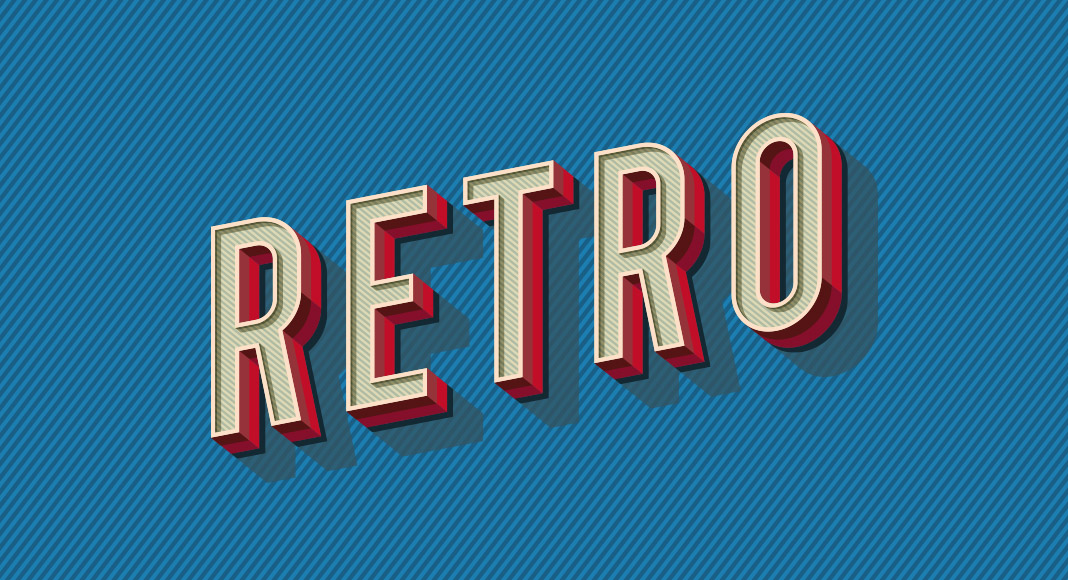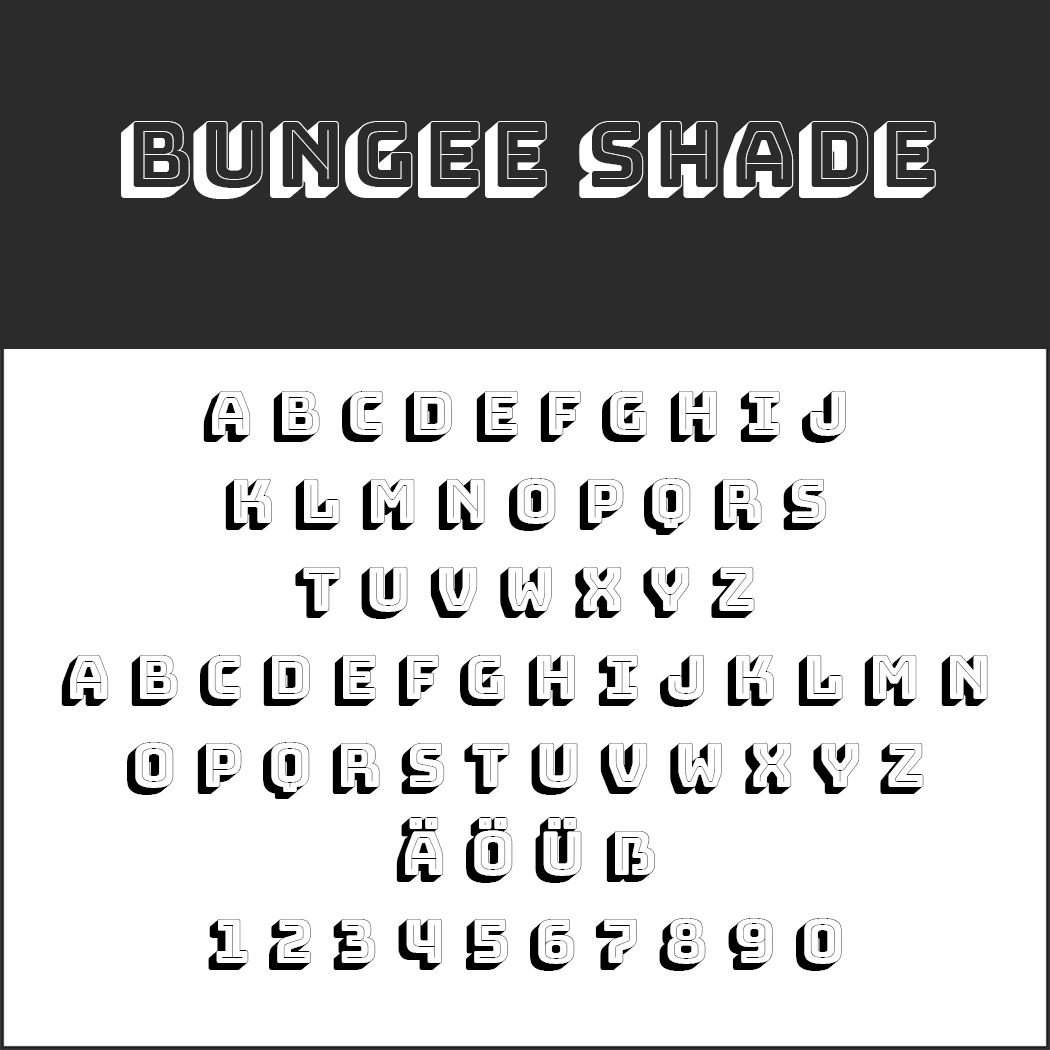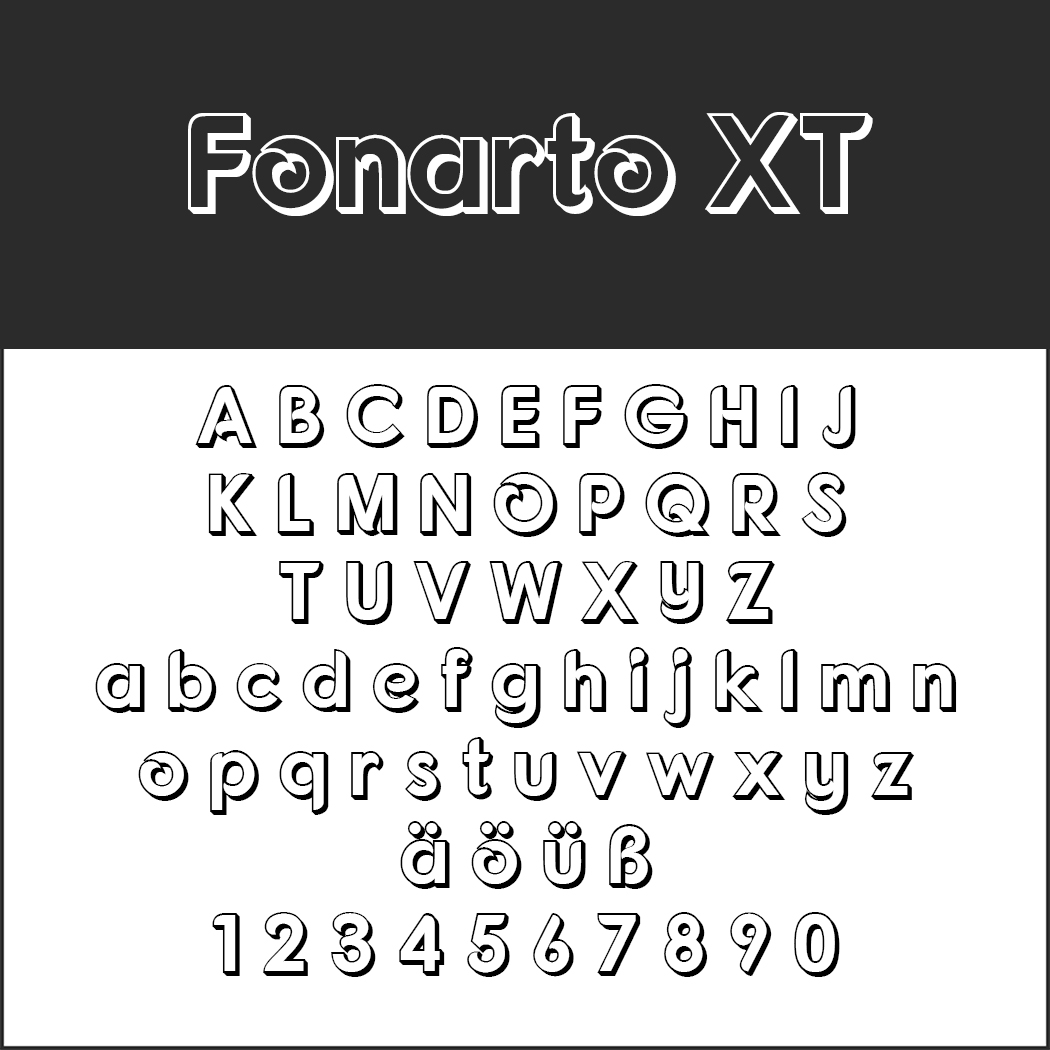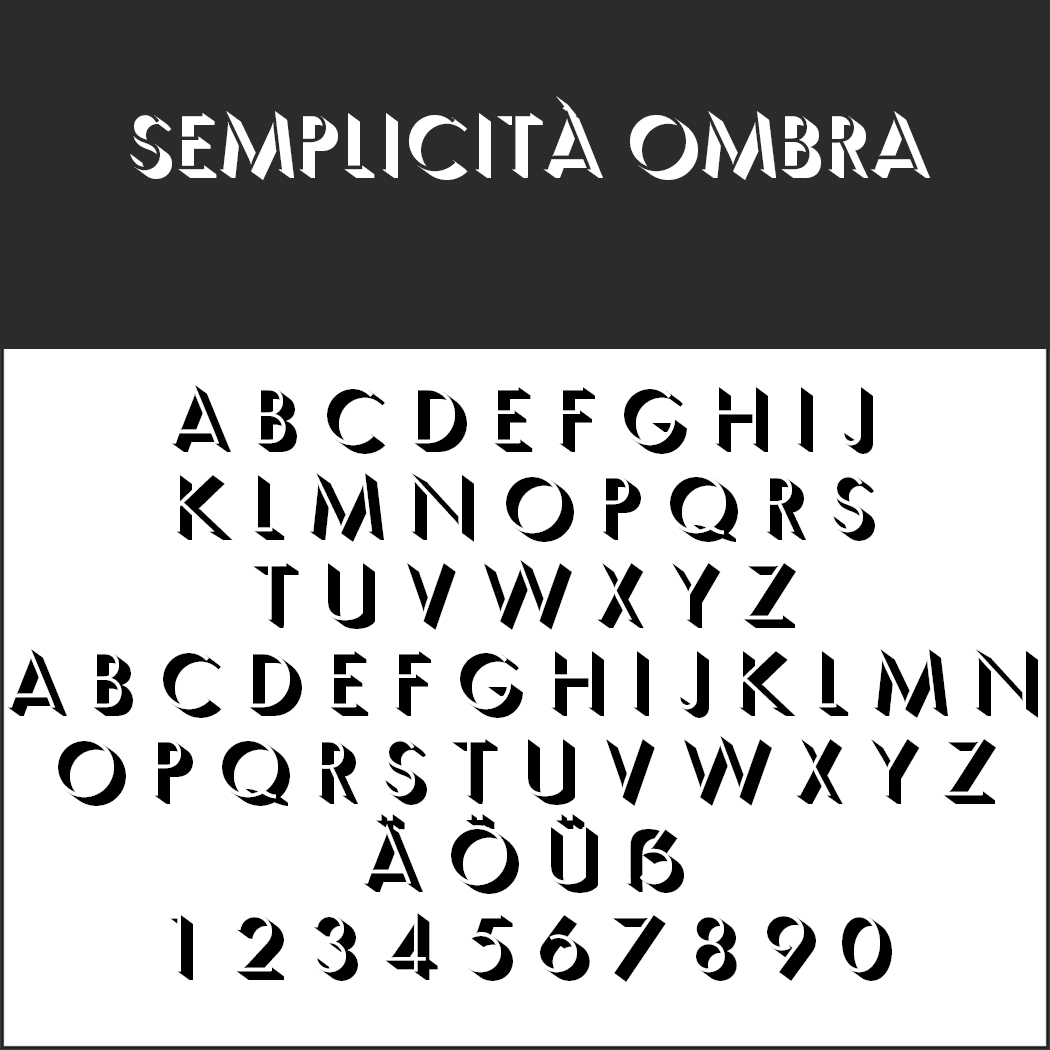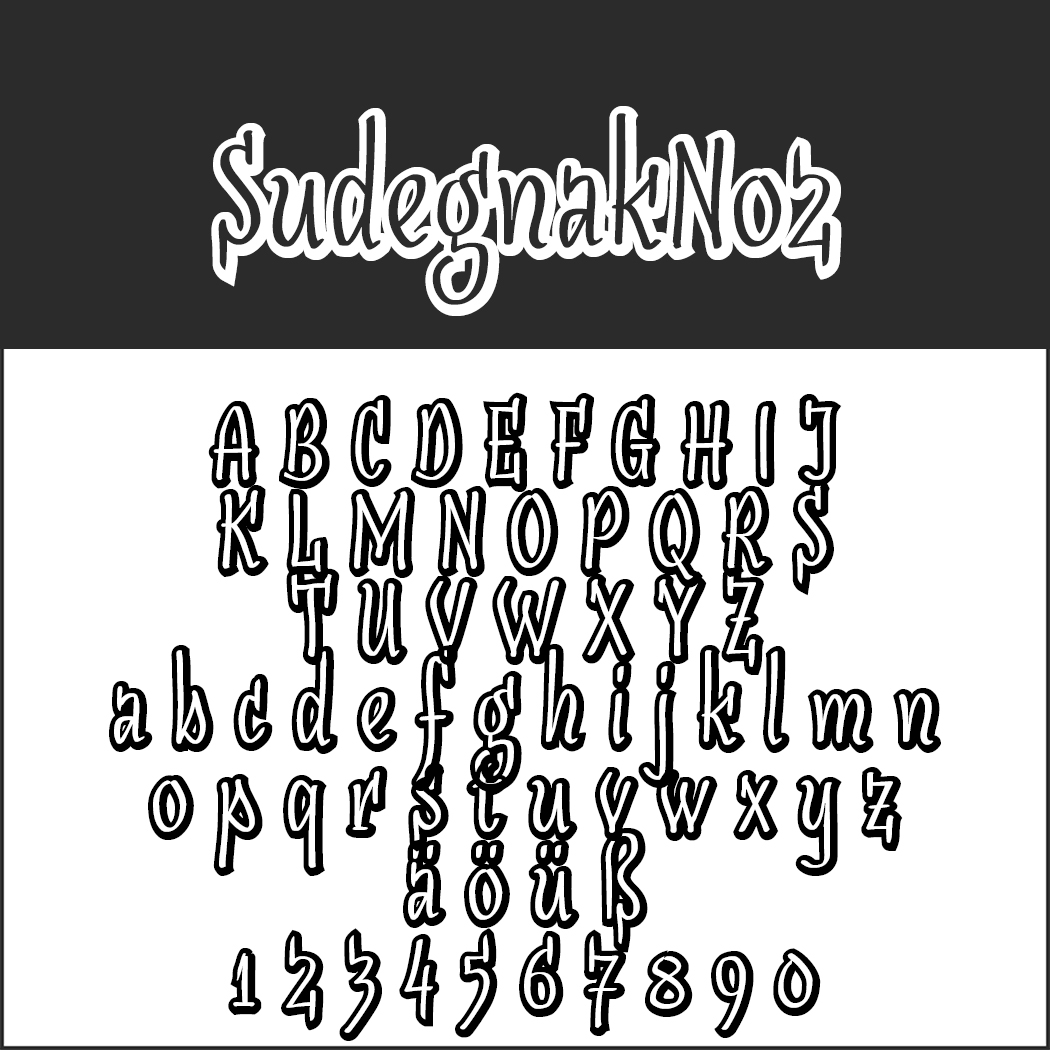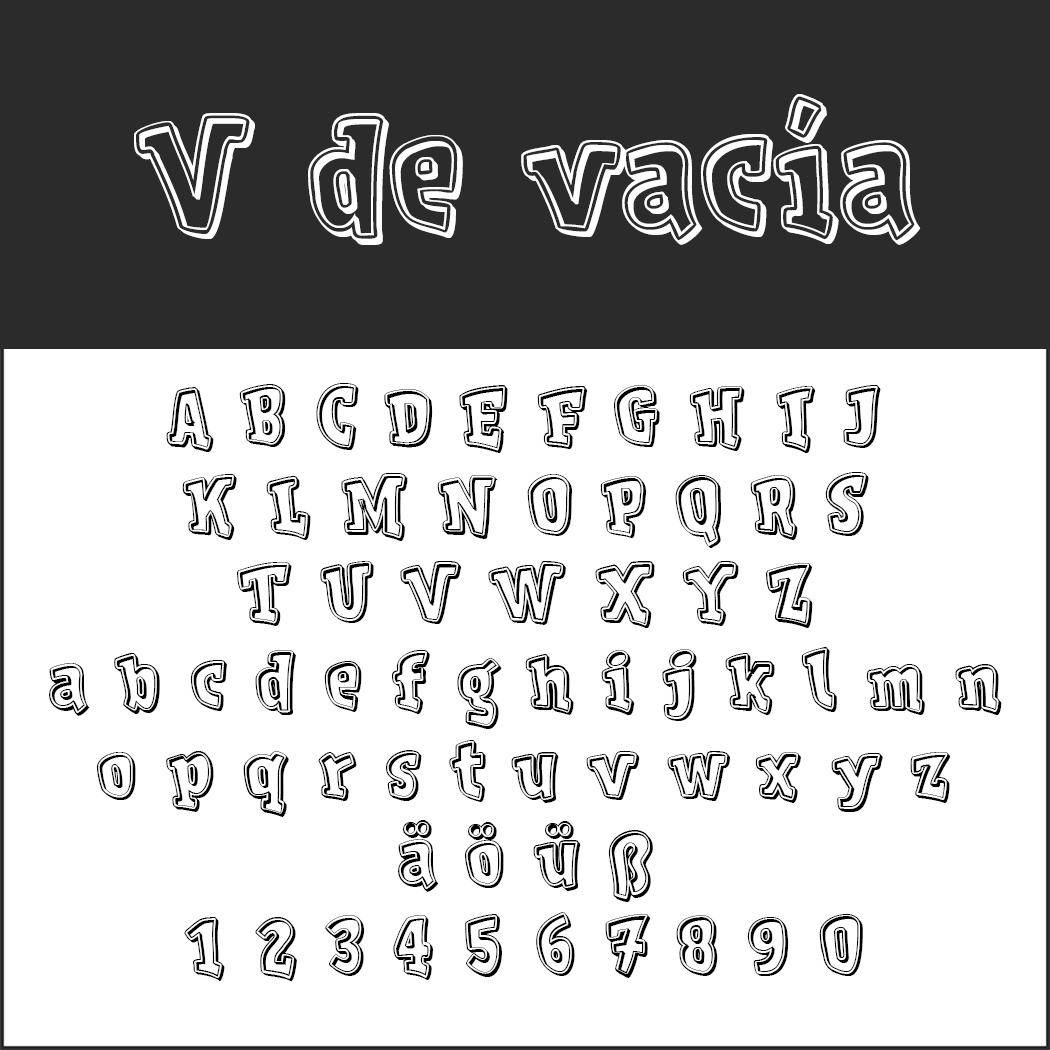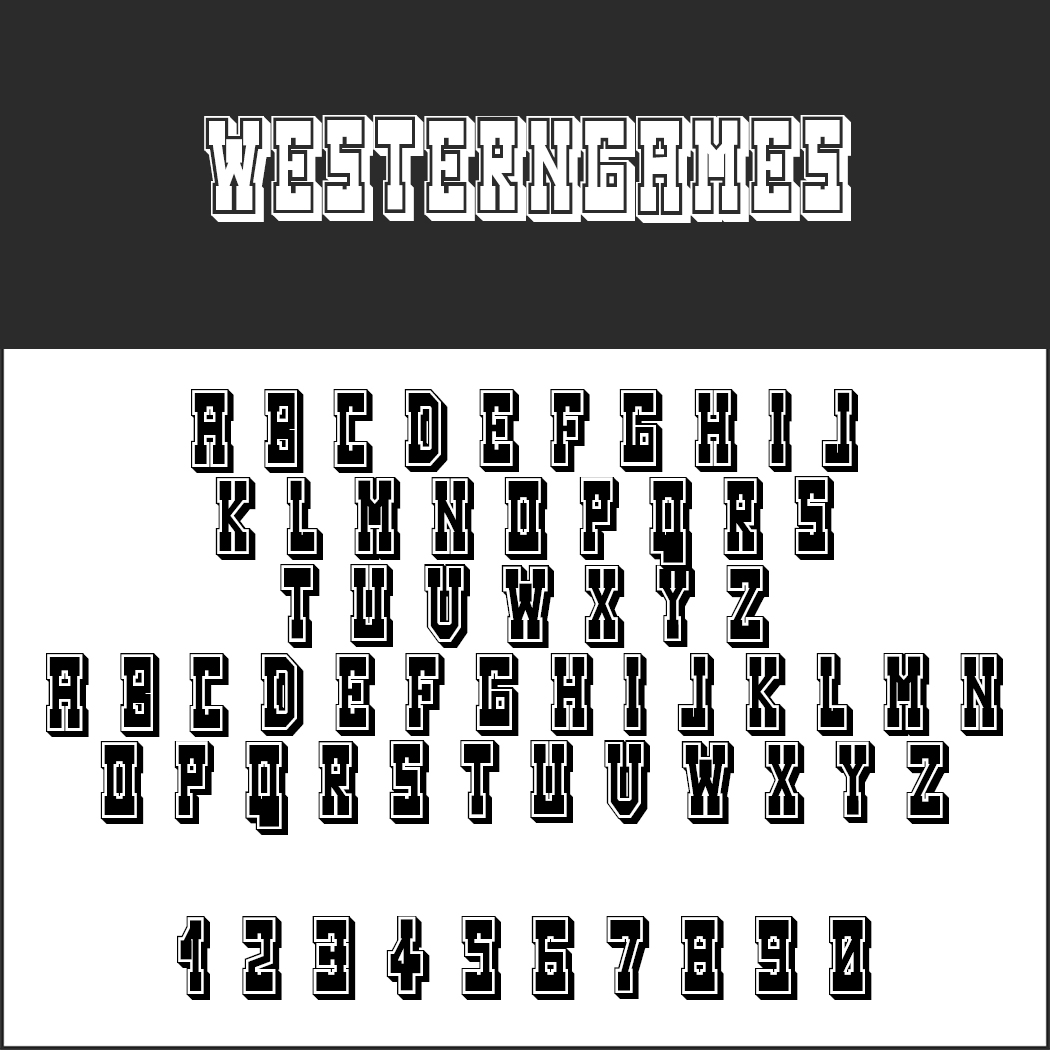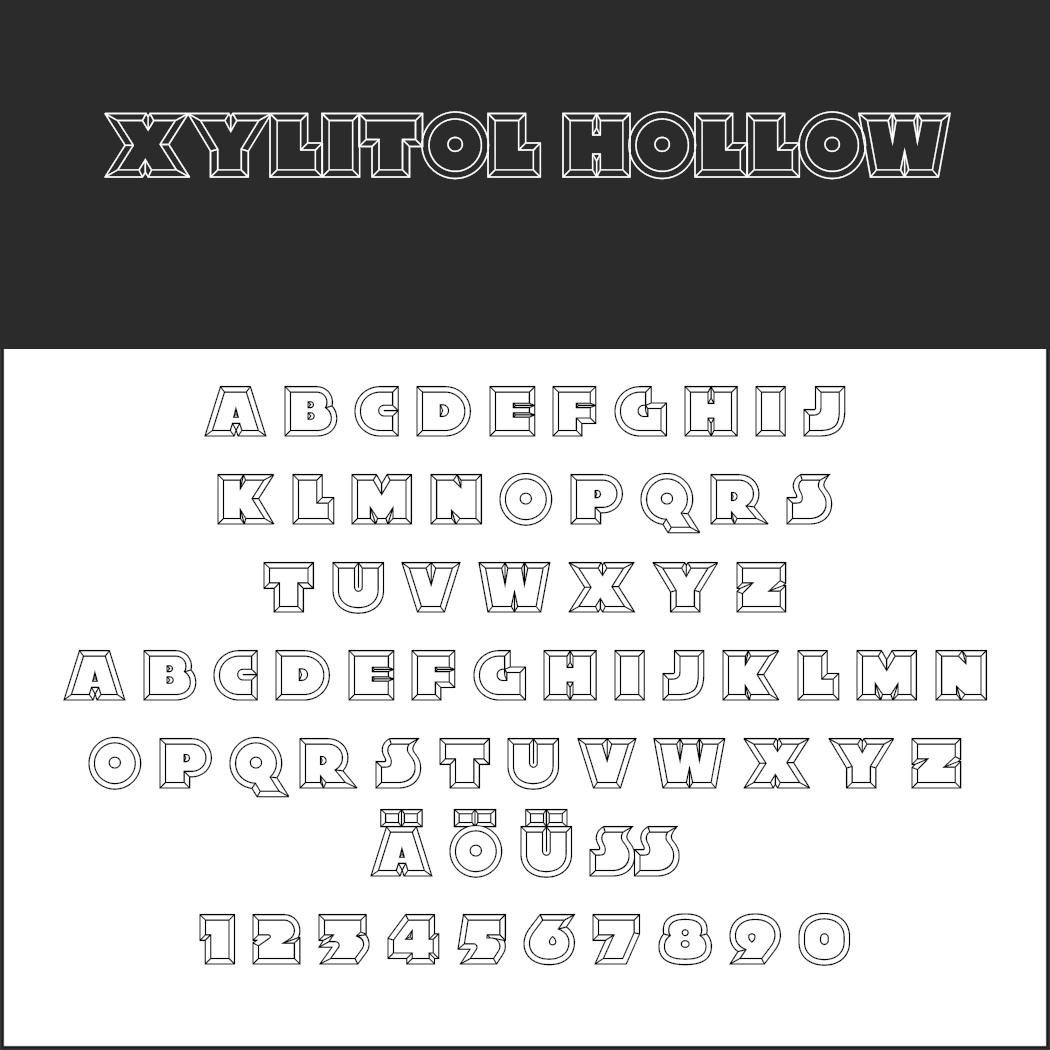
Korte budskaber vækker særlig opmærksomhed, hvis de består af tredimensionelle bogstaver. På papiret præsenteres de nemmest med en passende 3d font. Men med 3d font generatorer og særlige plugins i nogle programmer kan man også selv være kreativ. Her har vi samlet en oversigt over, hvordan man gør. Derudover er der et udvalg af gratis 3d font.
Det er mange årtier siden, at der dukkede skrifttyper med 3D-effekt op på biografplakater. De kan altså ikke betegnes som den allernyeste opfindelse. Alligevel vækker de til trods for nutidens mange designmuligheder den dag i dag stor opmærksomhed – i hvert fald, hvis de bruges målrettet. Den simulerede tredimensionalitet sørger ved korte, præcise budskaber for dybdevirkning, og den kan kombineres med mange forskellige skriftstile.
Men fordi der er lidt markedssælgerkvalitet over en 3d font, bør man overveje anvendelsen nøje: Passer den til emnet, målgruppen og det valgte format? På en plakat eller flyer har den sikkert en bedre effekt end f.eks. på et festskrift. 3D-effekter henvender sig nok mere til unge mennesker end til ældre, men med det store udvalg kan man principielt set ramme enhver smag.
Hvordan finder man den passende 3d font? Hvis man ikke lige råder over den perfekte font i ens eksisterende skriftpakke, kan man på internettet finde nogle udbydere, som i bedste fald endda tilbyder den ønskede skrift gratis. Vi har også et lille gratisudvalg til dig. Billeddatabaser tilbyder desuden vektorgrafik med 3D-effekt.
Så er der også muligheden selv at generere 3d font – med tilsvarende plug-ins i forskellige programmer. Det forudsætter dog en smule kunnen. Nemmere er det at bruge 3d font generatorer, som ikke kræver forhåndsviden.
Gratis 3d font til kommerciel brug
Udvalget af fonte med 3D-effekt på internettet er nærmest uendeligt, men henvender sig hovedsageligt til private brugere. Vi fokuserer her på fonte, som også kan bruges gratis til kommerciel brug. To eksempler finder du desuden under Fonts til plakater, som springer i øjnene.
Billedet viser 3D-Schrift Bungee Shade med navnet øverst og nedenfor alle store bogstaver (A-Z), specialtegn (Ä, Ö, Ü) og tallene 0-9 i skrifttypen på en hvid baggrund.
Bungee Shade
Shade-snittet af Bungee-skriften formidler en imponerende dybdevirkning, så man ved en passende størrelse og tilsvarende farver har indtrykket af at kunne gribe igennem bogstaverne. Bungee Shade anbefales således til plakatsøjler, fordi skriften også kan læses fra lang afstand.
En visning af Semplicità Ombra stencil-stil 3D-Schrift skrifttype, der viser store bogstaver A–Z, accenttegn (Ä Ö Ü) og tal 0–9 i sort på en hvid baggrund.
Semplicità Ombra
Det er helt afgjort divaen i vores fontudvalg: Selv hvis de første fire bogstaver i navnet ikke straks leder tankerne hen imod en stor opera, så skabes der associationer til en stor optræden. Den oprindelige Semplicità (ital.: enkelhed) blev designet 1930 i Italien og var rent faktisk ret simpel. I den digitale tidsalder fik denne skriftfamilie dog sin mondæne Ombra-variant.
• Design: Alessandro Butti (1930), for Ombra-snittet: Nebiolo
• Særegenhed: kun store bogstaver, men med ß
En sans-serif-skrifttype ved navn Fonarto XT vises i en fed, skitseret 3D-Schrift-stil med store bogstaver, små bogstaver, specialtegn (ö, ä, ü, ß) og tallene 0-9 på en hvid baggrund.
Fonarto XT
Med Fonarto ville den indonesiske designer, Arwan Sutanto, skabe en både moderne og klassisk skrifttype. Det er lykkedes for ham, som man kan se. Skriften er til trods for de fantasifulde detaljer nem at læse og passer til alle glade anledninger.
En visning af Xylitol Hollow 3D-Schrift-skrifttypen viser store bogstaver A-Z, bogstaver med accent Æ, Ö, Ü og ß og tallene 0-9 i en hul, konturstil på en sort og hvid baggrund.
Xylitol Hollow
Her kigger beskueren frontalt på bogstaverne. Det usædvanlige perspektiv øger ikke læseligheden, men sørger med velplanlagte farver for opsigtsvækkende effekter. Designeren giver i Readme-filen og på sin hjemmeside praktiske tips til brugen.
Alfabet i en legende 3D-Schrift-skrifttype med store og små bogstaver, specialtegn (ä, ö, ü, ß), tallene 0-9 og sætningen "V de vacía" øverst på sort baggrund.
V de vacía
De særpræget formede bogstaver fra V de vacía ser ud, som om de bliver vakt til live om lidt. Selv om den sanselige font stammer fra Nordspanien, råder den også over omlyd og ß. Den passer særlig godt til indhold, som lige som den selv går sine egne veje.
En fed, blokeret 3D-Schrift-skrifttype i vestlig stil vises. Eksempelteksten WESTERNGAMES vises øverst, efterfulgt af det fulde alfabet og tallene 0-9 med store bogstaver med tykke konturer.
Med Microsoft Word
Der kræves ingen særlig viden til anvendelsen i Word. Det fungerer lige så nemt som 3d font generatorerne. I fanebladet Tilføj klikker man på WordArt. Der åbnes en menu med forskellige 3D-stile. Når man har valgt en, vises et tekstfelt i den åbnede fil, hvor man skriver de ønskede ord. I fanebladet Start kan man som sædvanligt ændre skrifttypen, -størrelsen og -farven. Ved professionelle designs og især ved trykfiler bør man dog se bort fra „WordArt“.